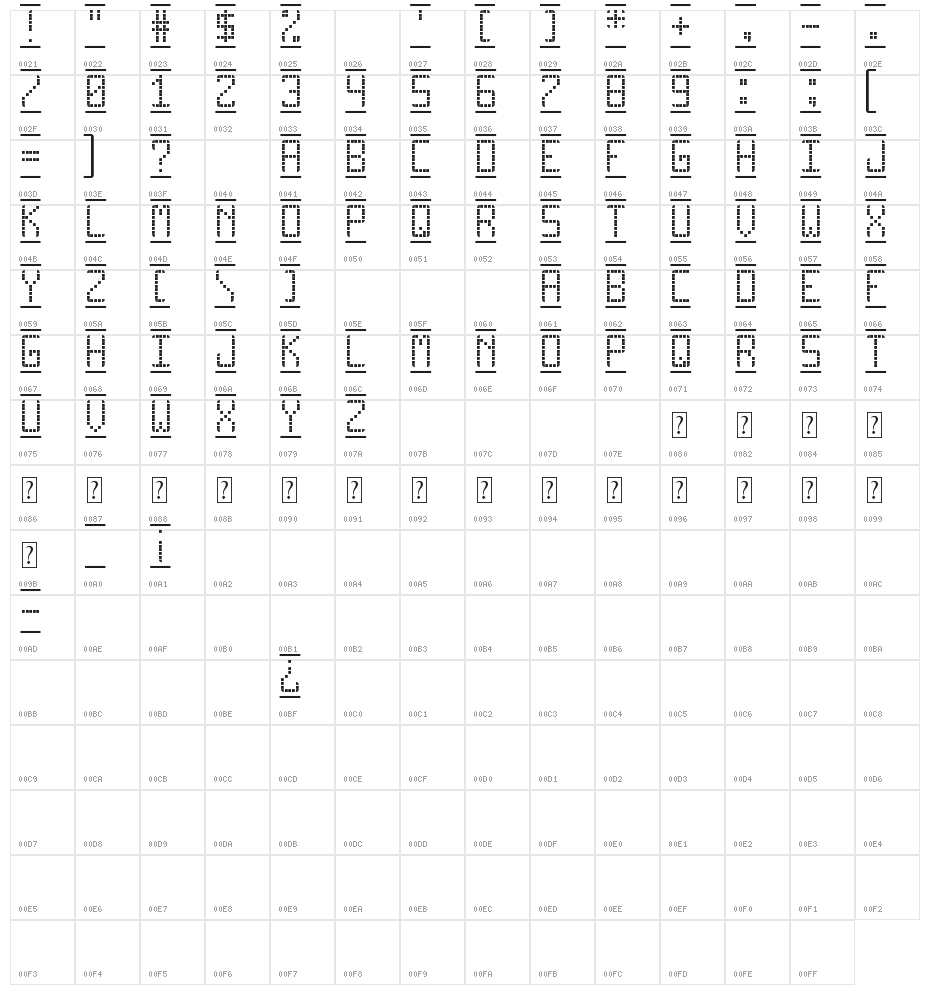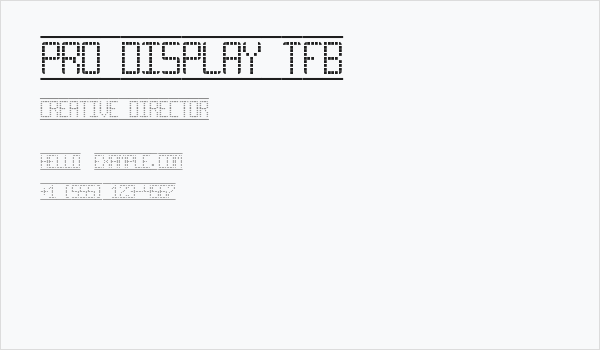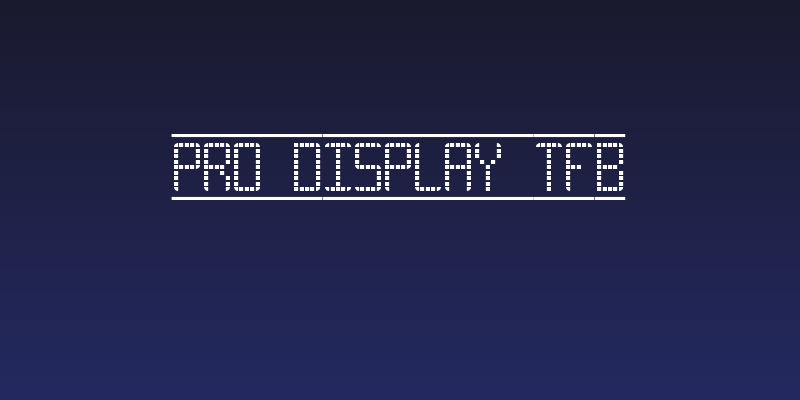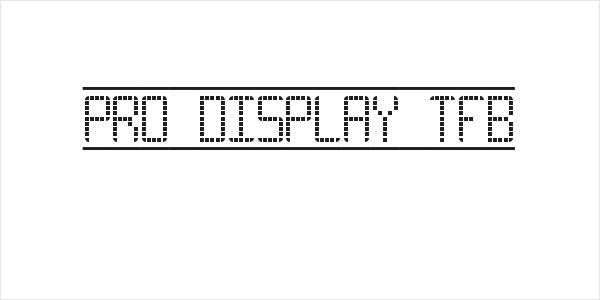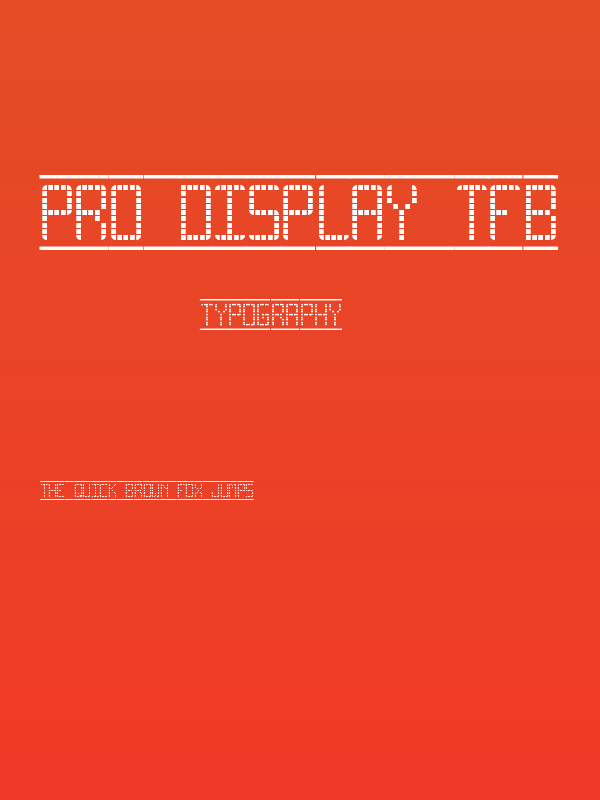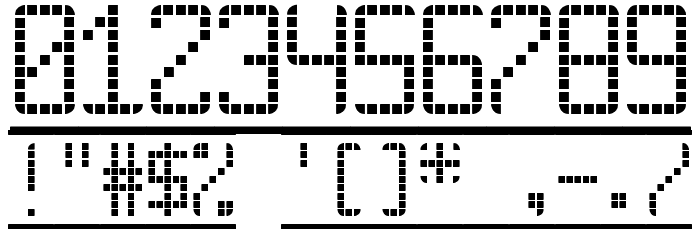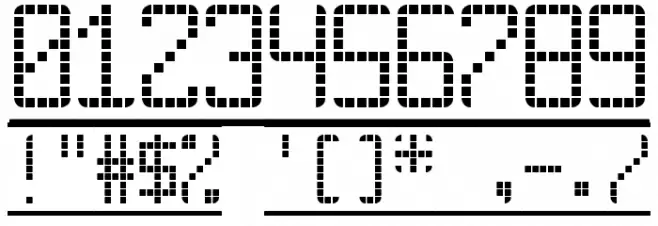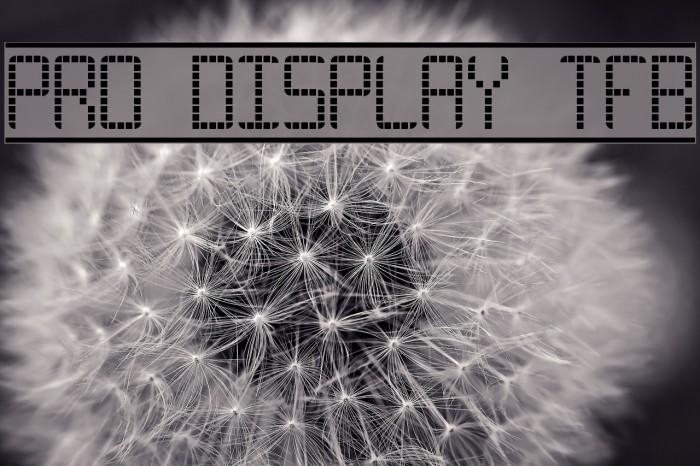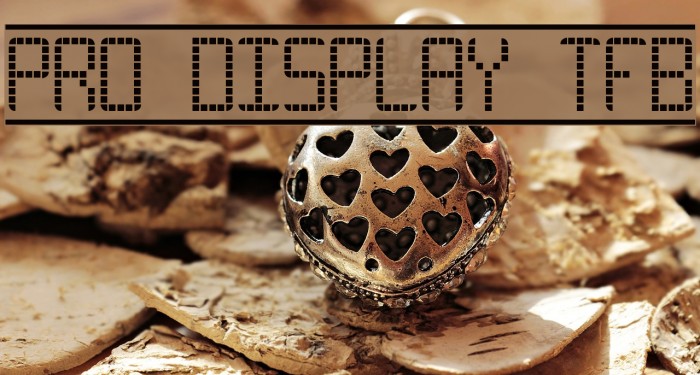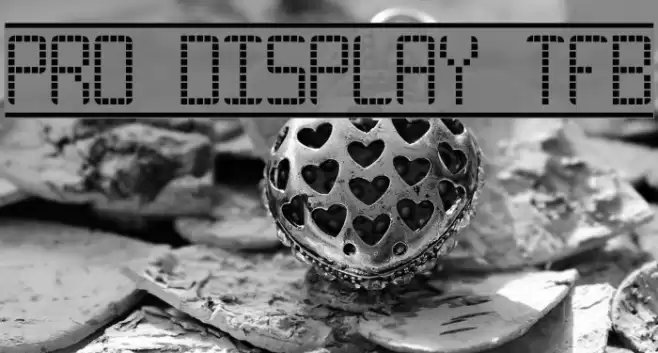
Pro Display tfb Font
| 用途 | Headlines, Logos, Digital Displays |
| おすすめプロジェクト | Ideal for digital displays, tech-themed designs, retro video game graphics, and futuristic branding. |